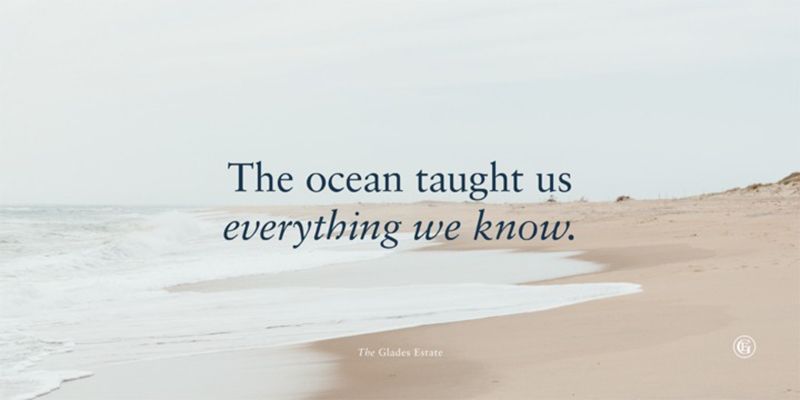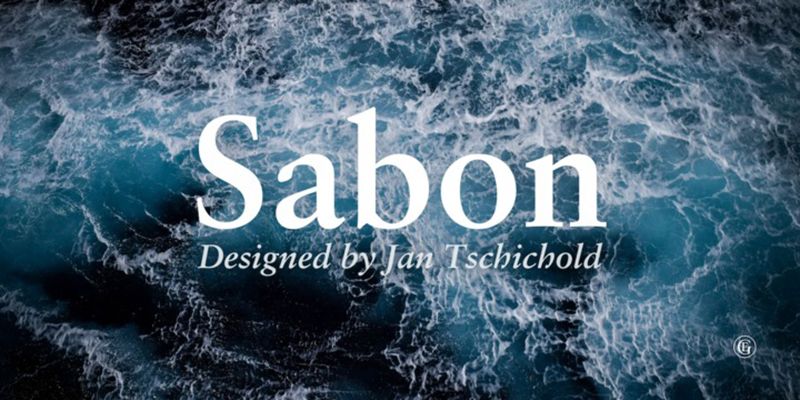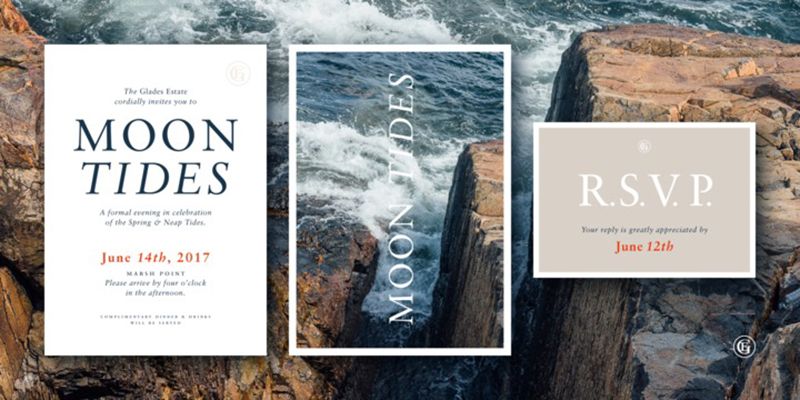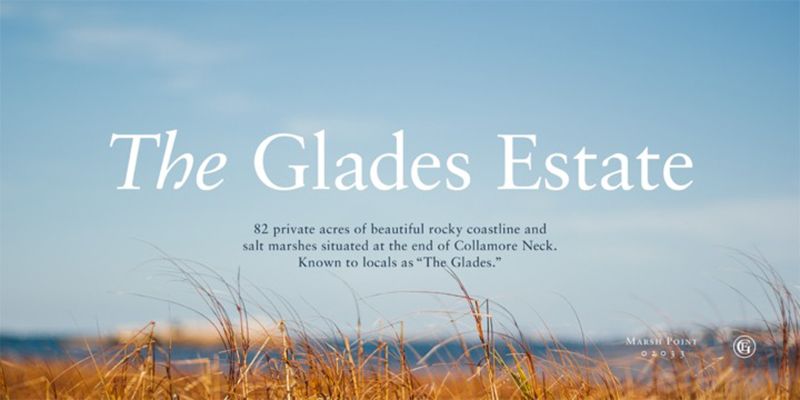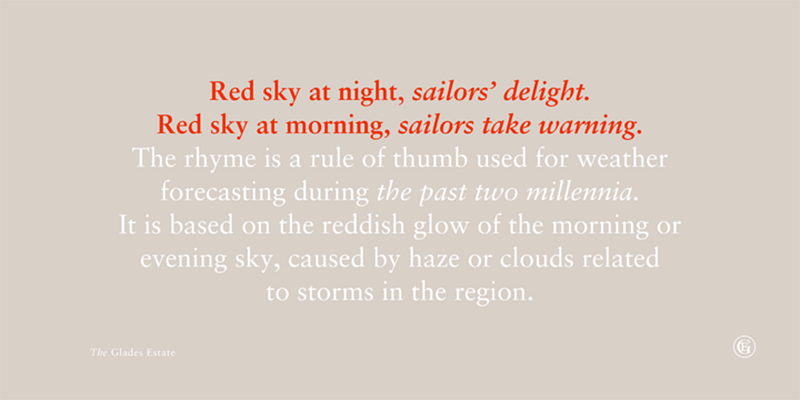
Die Sabon ist ein Nachfahre der Schriften von Claude Garamond und wurde 1964 von Jan Tschichold entworfen und von den Druckereien Stempel, Linotype und Monotype gemeinsam herausgegeben. Das römische Design basiert auf einem Garamond-Muster, das von Konrad F. Berner gedruckt wurde, der mit der Witwe eines anderen Druckers, Jacques Sabon, verheiratet war. Das kursive Design basiert auf den Schriften von Robert Granjon, einem Zeitgenossen von Garamond. Diese elegante, gut lesbare Schrift eignet sich hervorragend für anspruchsvolle Anwendungen, vom Buchdesign bis zur Corporate Identity.